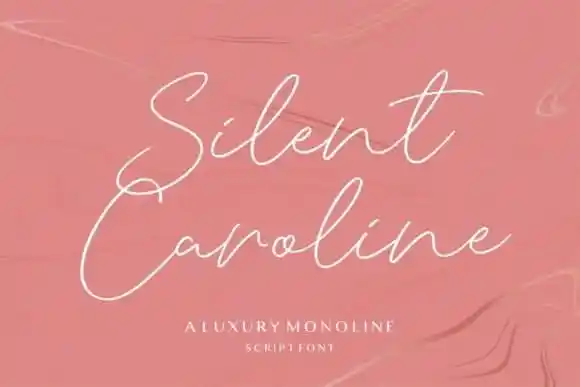
A fonte Silent Caroline Handwritten é uma elegante escrita curvilínea que combina modernidade com charme vintage. Através de sua linha monolítica, esta fonte é perfeita para criar projetos incrivelmente bonitos e única. Seu design foi criado pelo Letterative Studio, um conjunto de profissionais dedicados à criação de fontes de alta qualidade. Silent Caroline é uma escolha ótima tanto para aplicativos como produtos de embalagem, marcas, magazines, redes sociais, casamentos ou qualquer outra situação em que você deseja expressar as palavras acima do fundo. Seria um tesouro para adicionar à sua coleção de fontes.